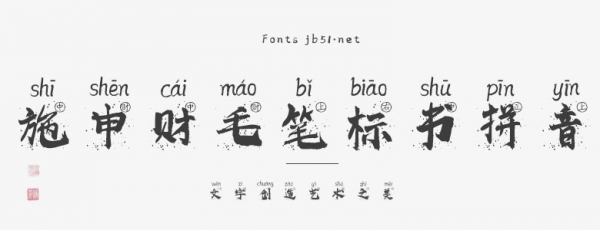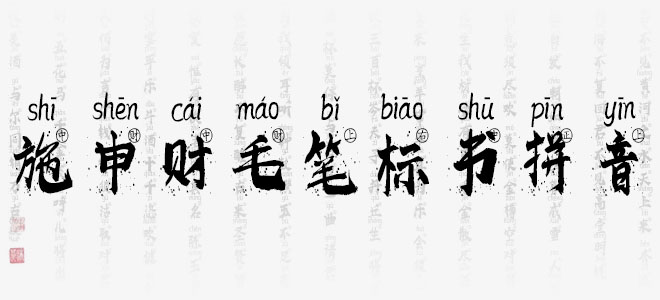
施申財(cái)毛筆標(biāo)書拼音是一款書寫很新穎的字體,自帶拼音標(biāo)注效果,具有強(qiáng)烈的視覺沖擊力。適用于海報(bào)、電商海報(bào)設(shè)計(jì)、店鋪設(shè)計(jì)、標(biāo)志設(shè)計(jì)、字體設(shè)計(jì)等領(lǐng)域。
施申財(cái)毛筆標(biāo)書拼音